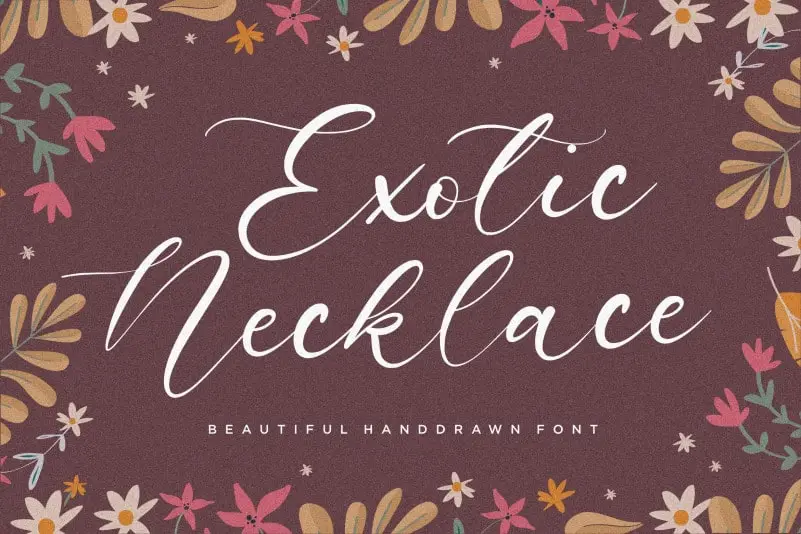
Exotic Necklace Handdrawn Font – Download Grátis
A fonte ‘Exotic Necklace Handdrawn Font’ é perfeita para qualquer projeto que busque uma aparição autêntica e criativa. Suas linhas fluidas e delicadas remetem a um colar exótico, combinando elegância com detalhes únicos. Seja você um designer de pacotes de produto, desenvolvendo um projeto de marca, redigindo o conteúdo de uma revista ou mesmo usá-la em redes sociais, para destacar mensagens importantes acima do fundo – esta fonte tem tudo que precisa. Com seu estilo elegante e delicado, ‘Exotic Necklace Handdrawn Font’ é perfeito para criar um impacto visual notável. Ela traz à vida textos de uma maneira única, deixando-os com um toque distintivo e inovador. É a escolha ideal para quem busca expressar personalidade e estilo em qualquer tipo de projeto. Não se esqueça que esta fonte é especialmente adequada para temas românticos ou temáticos, como casamentos ou revistas de viagens, onde um toque exótico pode trazer uma sensação única. Com ‘Exotic Necklace Handdrawn Font’, você está sempre no bom caminho para criar algo extraordinário e memorável.